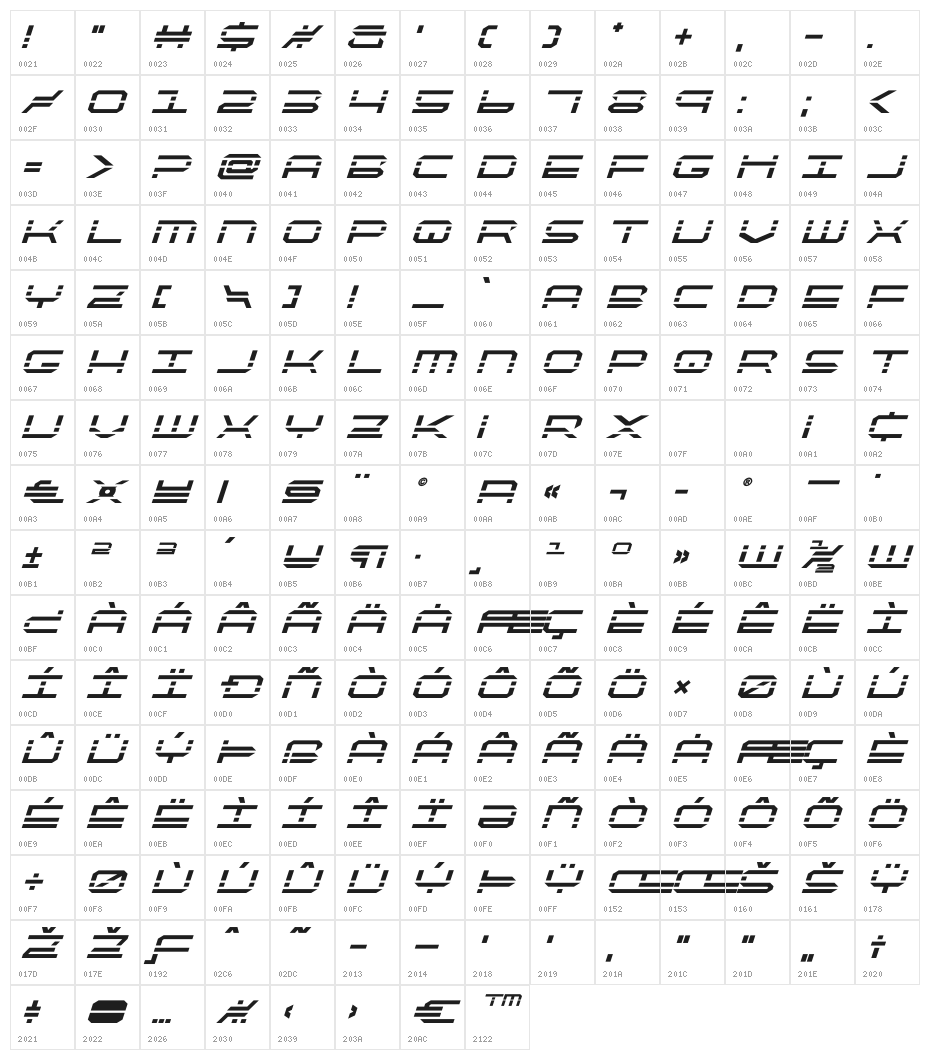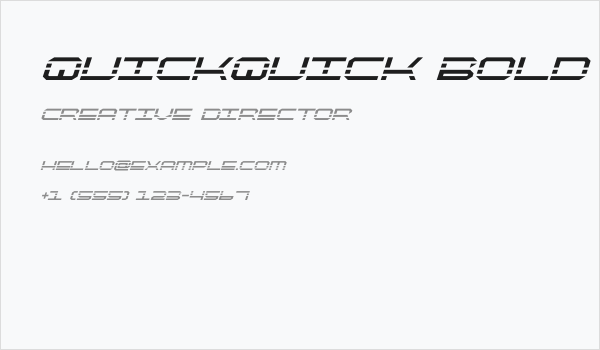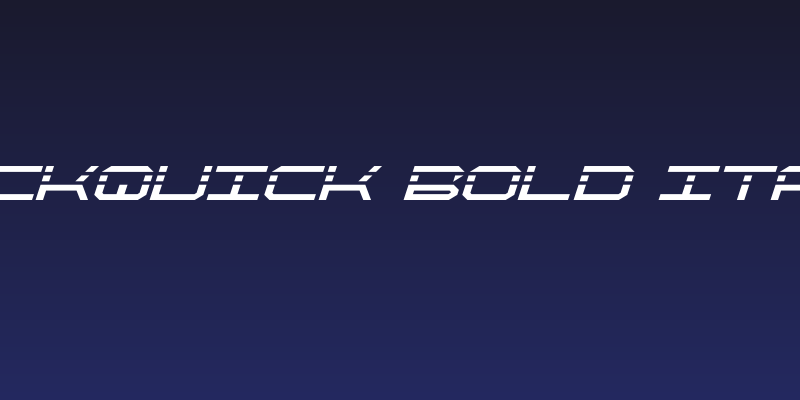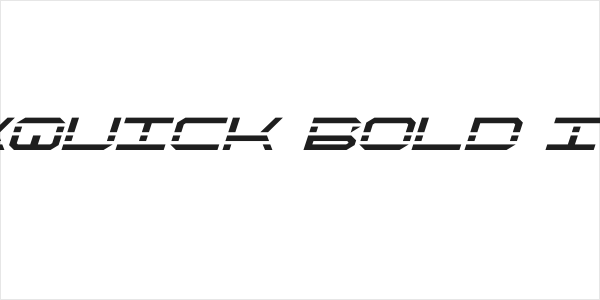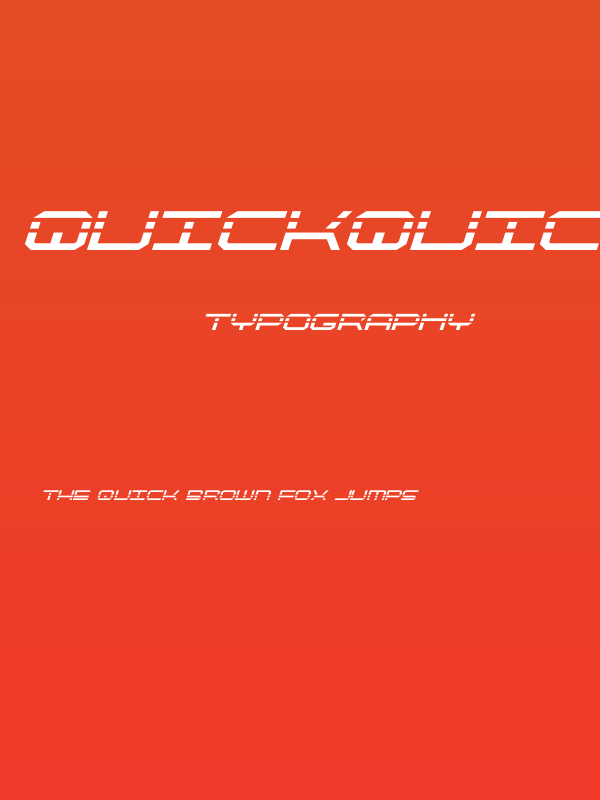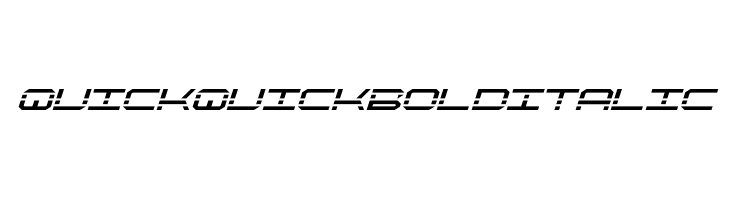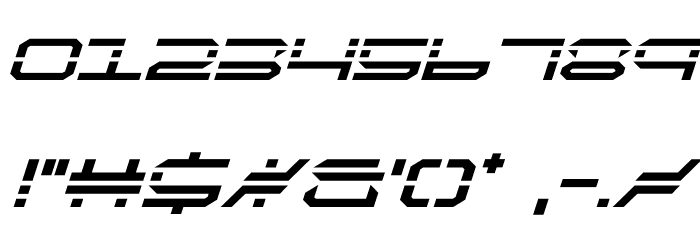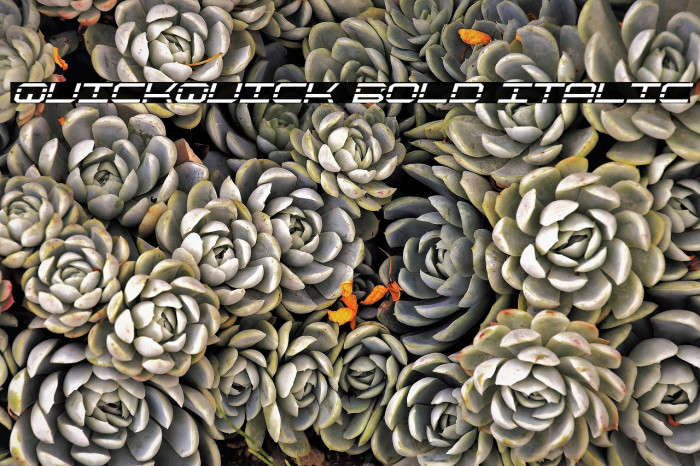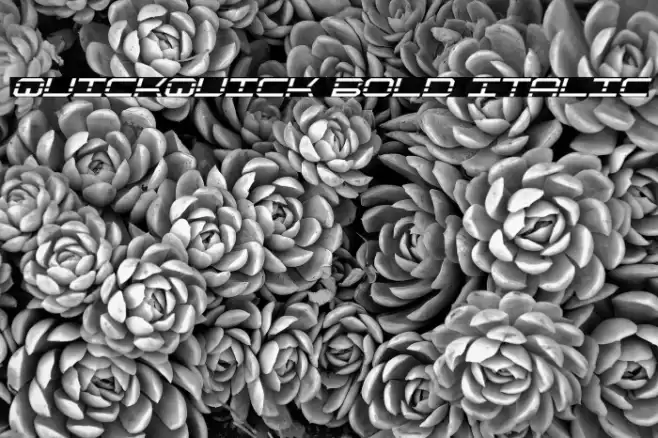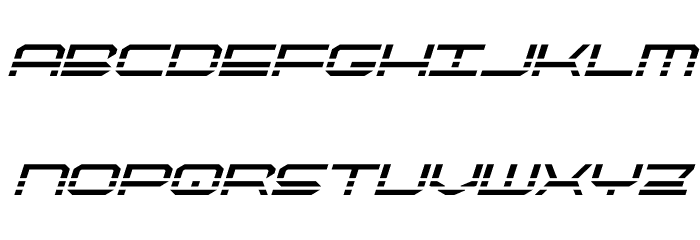
QuickQuick Bold Italic Font
| Anwendungsfall | Logos, Headlines |
| Vorgeschlagene Projekte | Ideal for technology branding, sports logos, and sci-fi themed designs. |